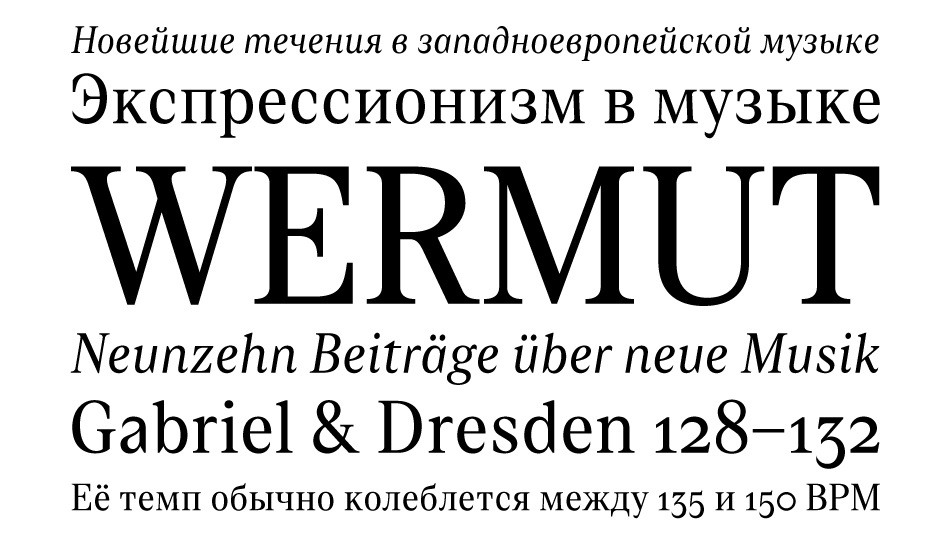
Журнал «Шрифт» • Десять шрифтов с кириллицей 2016 года
Почему бы в мае не вспомнить о прошедшем 2016 годе? Тем более что он был насыщен событиями как на глобальной, так и на локальной шрифтовой сцене. Вот некоторые из них. На конференции ATypI в Варшаве была представлена технология вариативных шрифтов, и, хотя об особенностях её применения споры не унимаются, очевидно, что отчасти будущее типографики где-то там.
Возможно, ответом на глобальный вызов Monotype (за покупкой FontShop последовало ещё два крупных приобретения: платформы визуального маркетинга Olapic и стартапа Swyft Media, зарабатывающего на эмодзи) явился Type Network — инициатива Font Bureau (Дэвид Берлоу и Роджер Блэк). В компании собран выразительный состав менеджмента и экспертного совета (в который вошли Дэвид Берлоу, Мэтью Картер, Петр ван Блокланд, Сайрус Хайсмит и другие).
Российский ландшафт тоже становится во многом интереснее: «ПараТайп» перезапустил магазин шрифтов Fonts.ru, в котором пользователям предложено сразу несколько оригинальных сценариев поиска и выбора шрифтов.
Разобравшись с флешбеком 2016-го, вернёмся к нашему ежегодному обзору. Условия выбора проектов остались прежними: шрифт должен содержать набор кириллических знаков, право на его использование должно быть доступно для приобретения любому желающему, дата выпуска — не ранее января и не позднее декабря 2016 года. На этот раз дополнительно к десятке мы решили собрать небольшой арьергард из 9 шрифтов, а авторам шрифтов задали пару вопросов:
Итак, все 10+9 в алфавитном порядке☟
Дизайнеры: Арина Алафердова, Дмитрий Кирсанов.
Издатель: ParaType, Россия
Крупнокегельная версия шрифта Baskerville вышла в компании «ПараТайп» в сентябре 2016 года в комплектах Display и Poster. Базовые параметры гарнитур унаследованы от ITC New Baskerville, так что они составляют хорошую пару к 8 начертаниям от Джона Квартанта и Ко, сделанным в ITC в 1972 году (кириллический набор знаков был создан Тагиром Сафаевым в 1993-м). Обострённый контраст, зауженные пропорции знаков, тонкие детали (особенно примечателен курсив в Baskerville Poster) предполагают работу в крупных кеглях — и в этом масштабе Baskerville Display & Poster приобретают неприличную красоту и изящество. Можно сказать, что авторам удалось максимально претворить стремление Джона Баскервиля к тонкой и выразительной форме. Среди прописных знаков курсива можно обнаружить и альтернативные формы со свошами и росчерками, напоминающими нам о том, что сам Баскервиль был прекрасным каллиграфом.
Шрифты Baskerville и сегодня остаются рабочей лошадкой многих типографов. С советских времён (если говорить о кириллической версии) комфортные пропорции, спокойные и привычные формы этой гарнитуры встречаются на страницах детских книг, художественной литературы, документальной прозы, журналов. Эти шрифты сложно назвать остроактуальными, но они всегда будут присутствовать в арсенале дизайнера, оформляющего книгу. И теперь с появлением тщательно отрисованных крупнокегельных версий дело остаётся за умелым применением этих шрифтов не только в заголовках и на титульных страницах книг, но и в журналах, инфографике и прочих жанрах — без стеснения в кеглях и размерах.
Дизайнеры: Ольга Панькова, Илья Рудерман. Издатель: type.today, Россия
Этот неогуманистический гротеск с беспрецедентным для текстового шрифта количеством лигатур (как в латинице, так и в кириллице) был разработан по заказу журнала «Большой город». В интервью с Ильёй Рудерманом мы уже рассказывали о роли этого шрифта в издании: «Гротеск Big City сделал немало и для литературного, и для гражданского образа журнала. Во многом этому способствовала актуальная типографика с долей самоиронии, что в целом отвечало и духу индивидуальности личности, и демократизму, которые провозглашал БГ». На тот момент гарнитура содержала 11 начертаний (9 прямых и два курсивных). В 2009 году Big City стал победителем международного конкурса Современная кириллица. Шрифт долгое время оставался в эксклюзивном использовании редакцией журнала, затем начался долгий процесс доработки гротеска с участием Ольги Паньковой для публичного релиза под лейблом
В 2016 году шрифт был представлен в девяти насыщенностях (от Hairline до Heavy) с соответствующими курсивами (всего 18 начертаний). В новой версии уточнён рисунок знаков, добавлена капитель, новые лигатуры и неалфавитные символы. Если принимать во внимание, что гарнитура поддерживает более 100 языков, а лигатуры присутствуют не только в строчных, но и в прописных знаках и в капители, то грубый арифметический подсчёт даёт более 2000 лигатур в одном начертании. Умножая на общее количество насыщенностей, мы получаем астрономический объём работы, которая была проделана для того, чтобы выпустить шрифт в продажу.
Типографический потенциал этого гротеска выглядит весьма впечатляющим. Кроме необъятного количества лигатур он оснащён символами, чувствительными к регистру, всеми видами цифр, числительными, дробями, индексами, математическими знаками ключевых валют.
Стимулом к работе послужила моя стажировка в CSTM Fonts, и я была счастлива, что Илья и Юра (Илья Рудерман и Юрий Остроменцкий.
— Прим. ред.) доверили мне именно этот шрифт. Во-первых, я фанат одноимённого журнала и до сих пор храню много номеров, а во-вторых, после долгой работы над Пулитцером было очень интересно поработать с гротеском, и особенно с лигатурной частью. Поначалу страшнее всего было вносить даже минимальные изменения в контуры, ведь этим шрифтом долго набирали журнал и он прекрасно работал! Но поскольку я всё делала под чётким руководством Ильи, больших сложностей не возникало. Думаю, всё, чему я научилась в процессе создания такой большой семьи, можно считать достижениями.
Дизайнер: Александра Королькова. Издатель: FontFont, Германия
Наследник шрифта Belladonna (эксклюзивный проект для журнала Italia), гарнитура FF Carina — это вариация на тему антикв нового стиля XVIII–XIX веков. Монументальная симметрия и статика, высокий контраст, зауженные пропорции знаков — все признаки, присущие дидонам, мы видим и здесь.
Однако изобретательная работа с остроконечным пером привела к уникальному образу. Необычная пластика графем, наплывы овалов с энтазисом, чернильные сталагмиты и сталактиты засечек в прописных C, E, F, G, S, T, Z, кокетливые капли в строчных знаках — и вся неоклассика летит к чёрту, а взгляду открывается эстетика журнального леттеринга 1970-х в исполнении Герба Любалина и, например, шрифт ITC Tiffany Эда Бенгета.
Декоративность внедрена в шрифт по его же законам — лигатуры, своши, минускульные цифры и некоторые альтернативы развивают характер шрифта. Отдельного отметим альтернативный ноль в волос толщиной и кириллические лигатуры, сделанные без стремления соединить всё со всем. FF Carina поддерживает почти сотню языков, она простроена в трёх начертаниях (Regular, Bold, Black), содержит дроби и математические знаки (хотя сложно предположить, что гарнитуру будут использовать в контексте, в котором потребуются дроби и индексы).
…Арт-директор «ПараТайпа» публикует шрифт в «ФонтШопе»? В этом нет никакой конспирологии. Предложение лицензировать будущий шрифт поступило автору от FontShop на конференции ATypI ещё в 2008 году, и спустя годы Александра сдержала своё обещание.
Дизайнер: Валерий Голыженков. Издатель — type.today, Россия
Акцидентное начертание шрифта Futura Display (как и формы Futura Black), выпущенное Паулем Реннером в 1932 году, очевидно, уже навсегда останется в тени основного комплекта стилей этого геометрического гротеска. Более того, этот квадратный упрощённый шрифт в современной логике проектирования шрифтовых семейств не имеет общей конструктивной и графической основы с Футурой.
Обращение Валерия Голыженкова к неочевидной стороне Футуры привело к проверке потенциала и возможностей этой графики. Сначала First Prize производит впечатление реплики на реннеровские формы, но, разглядев детали проекта, понимаешь, что здесь работа велась совсем в другом направлении.
Автор ставит перед собой задачу «генетического» эксперимента. Да, в основе работы — жёсткая логика геометрического гротеска (First Prize лишён даже скруглений внутренних овалов, а внутрибуквенное белое вырублено под прямым углом), но самое нтересное начинается с момента внедрения в эту графику конструкций наклонного и прямого курсивов (Bold Italic, Bold Upright). Добавить сюда цитирование некоторых особенностей старостильных антикв (верхние выносные элементы выше прописных, минускульные цифры), игры с начальными и концевыми росчерками — и идея доводится до возможного абсолюта.
В результате получился акцидентный шрифт, который в любом макете решительно возьмёт на себя роль солиста. И если начертание Bold действительно напомнит нам о Реннере, то Bold Italic и Bold Upright — это настоящий Голыженков. Если вам доводилось видеть его быстрые наброски шрифтовых форм (на бумажных скатертях в кафе, например), то вы поймёте, что синтез каллиграфии и шрифтовой инженерии — это характерная особенность его авторского темперамента.
Шрифт способен держать как экстремально крупные кегли, так и среднекегельный набор (в умеренных количествах) и обладает всем потенциалом для развития в сторону светлых начертаний. В любом случае First Prize уже занял место в ряду состоявшихся шрифтовых экспериментов.
Импульсом для начала работы могу назвать два момента. Первый — желание дать новую жизнь одному из моих старых шрифтов. В результате FirstPrize 2000 года выпуска был полностью перестроен. Второй момент — это интерес, который проявили к шрифту Илья и Юрий (Илья Рудерман и Юрий Остроменцкий. — Прим. ред.) во время просмотра и обсуждения кандидатов для релиза на площадке type.today. Признаюсь, без их поддержки шрифт мог бы надолго задержаться в столе среди прочих набросков. На сегодня удалось подготовить две группы связанных между собой начертаний, каждая из которых привязана к FirstPrize Bold.
Одна группа — это начертания зауженных пропорций, вторая состоит из сильно сжатых начертаний.
Сложности? Это, наверное, самый объёмный из моих проектов, и сложнее всего было на стадии технической разработки и тестирования, когда все основные идеи были уже реализованы — нужно было не отвлекаться на другие, более творческие задачи.
Дизайнеры: Винсент Чан, Кристиан Шварц, Илья Рудерман (кириллица). Издатель: Commercial Type, США
Дизайнеры Винсент Чан и Кристиан Шварц спроектировали этот гротеск в 2008 году по заказу Кристофера Мартинеза, арт-директора журнала о моде и стиле T (The New York Times Style Magazine). Журнал Т укоренён в культуре и визуальной истории большого американского мегаполиса. Хотя он был запущен в 2004 году, связь издания с NYT наводит на соображения, что каждый редизайн Т немыслим без доли консерватизма и поисков интеллигентных ходов.
Первый шрифт семейства Giorgio (2007) с засечками, который арт-директор T-magazine Кристофер Мартинез наметил для заголовков, получился коктейльной гарнитурой с благородной историей. В нём смешаны высокий контраст, геометричность, несколько эксцентричных деталей в альтернативных знаках. Характерная особенность — минимальная разница между высотой строчных и прописных знаков и короткие выносные элементы. Отсылка к 1930-м была очевидной — по словам авторов Giorgio, многие решения они переняли из гарнитуры Corvinus (Bauer Type, ок. 1935) швейцарского дизайнера Имре Райнера. Это было время ненависти к орнаменту — Корвинус сделан минималистично и обладал своеобразным ритмом.
Генетика Giorgio Sans того же порядка — узкий гротеск с короткими выносными элементами, который в наборе сбивается в плотные строки, напоминающие о типографике модных журналов 20-х и 30-х годов.
Он более «полиграфичен», универсален и не претендует на связь с историей, городской средой и афишами века джаза. Отдельный сет круглых и более широких прописных знаков позволяет играть с ритмами заголовков — приём, которым уже увлекались журнальные дизайнеры (не стоит забывать, что шрифт был сделан для макета десятилетней давности). Кроме того, латиница содержит четыре альтернативных знака G, Q, R и g, а в кириллице только буквам Я, я повезло иметь вариацию.
Можно сказать, что это шрифт для ручного набора — диапазон насыщенностей (9 начертаний с курсивами) предполагает побуквенную сборку акциденции, взаимодействие её с графикой и фото, тонкую работу с белым пространством листа, огромным пятном, конструкцией. Чем громче, тем лучше, но нет ничего скучнее монотонного текста, аккуратно набранного Giorgio Sans в небольшом кегле.
Дизайнеры: Манвел Шмавонян и Александр Любовенко. Издатель: ПараТайп, Россия
Mediator — необходимое и ожидаемое приближение к универсальным гарнитурам вроде Frutiger или Univers, которых по-прежнему не хватает на рынке кириллицы. Это неогуманистический гротеск со спокойной (на первый взгляд) пластикой, и его главные качества — удобочитаемость в мелких кеглях и лёгкость сочетания с книжными антиквами различного рисунка и темперамента.
У шрифта открытая апертура, разница между высотой прописных и строчных знаков существенная, как и высота выносных элементов. Прописные буквы равноширинные; образ шрифта в кириллическом наборе чем-то напоминает Humanist 531 (кириллическая версия шрифта Syntax Ганса Эдуарда Мейера, 1968). Возможно, это уже авторский почерк — оба шрифта были сделаны Манвелом Шмавоняном. Вопросы вызывают разве что зауженные начертания Narrow и Condensed: в таких тисках динамичные формы начинают «скрипеть», все изгибы, дуги, диагонали деформируются, а размашистые выносные элементы сопротивляются попыткам собрать немногословную композицию.
По словам издателя, Mediator — незаметный шрифт, но, по нашему мнению, в текстовых кеглях он достаточно эмоционален и выводит свою, совсем не медитативную мелодию. Это нужно учитывать при выборе шрифта в качестве как основного, так и вспомогательного инструмента для набора. Гарнитура содержит 30 начертаний: 8 прямых и 8 курсивных от Thin до Black, 7 зауженных и 7 узких от Thin до ExtraBold. В комплекте минускульные цифры во всех начертаниях и капитель в прямых начертаниях нормального диапазона.
У меня давно зрела мысль сделать шрифт большого диапазона с довольно широкими пропорциями. Я и раньше проектировал шрифты с большим количеством начертаний, но в таком диапазоне — начиная с Thin до Black — впервые. По большей части я проектирую текстовые шрифты. И в этот раз мне хотелось создать современный текстовый гротеск. Сложность была в том, что очень трудно выделиться в том количестве шрифтов, которые уже существуют и разрабатываются сегодня дизайнерами.
Я стараюсь выделяться отточенностью моих шрифтов. Насколько это у меня получается — судить не мне.
Дизайнеры: Петер Билак, Ирина Смирнова (кириллица). Издатель Typotheque, Нидерланды
Петер Билак поставил перед собой довольно практичную задачу — создать рациональный шрифт, который работал бы в длинных текстах так же хорошо, как и в заголовках и навигации. Подобно шрифтам для систем ориентирования, November спокоен и лишён ярких отвлекающих деталей. «Порой шрифт должен просто хорошо справляться со своими обязанностями», — комментирует Билак свою задачу.
Достаточно взгляда на состав шрифтовой семьи, чтобы убедиться в её мультифункциональности. Три группы начертаний (Normal, Condensed, Compressed) в диапазоне от Hairline до Black; капитель, минускульные цифры, индексы, регистрозависимые альтернативные знаки дадут необходимую свободу дизайнеру в работе с любой типографической задачей.
Добавить к этому кириллицу (дизайн Ирины Смирновой), греческий и иврит (консультации Даниэля Грамера) — и применение шрифта расширяется до 200 языков.
С набором массы от начертания к начертанию шрифт обретает темперамент, проявляя хоть и сдержанный, но довольно открытый и дружелюбный нрав. Среди цифр на себя обращают внимание 6, 8 и 9, которые, будто игнорируя соседей, выведены из круга с геометричной точностью. В светлых начертаниях видна точная работа Билака с характером овалов и формой. Позволив себе грубое обобщение, этот шрифт можно было бы назвать голландским DINом, в котором верх берёт не инженер, а прагматичный художник.
Работа над кириллицей к November шла на удивление легко. Не знаю, помогал ли мне предыдущий опыт — работа над суперсемейством Greta Sans или сам рисунок шрифта.
Единственная форма, которая нашлась не сразу, — это строчная б. Лаконичность форм не позволяла добавить привычный изгиб вверх в окончании выносного элемента. Диагональный штрих требовал другого среза, а горизонтальный выносной элемент без изгиба делал форму больше похожей на шестёрку. Я нашла тот минимальный наклон, который создал необходимое движение по диагонали вверх и позволил закончить штрих строго вертикально. Когда я стала тестировать готовый шрифт, то поняла, что November действительно не обращает на себя внимания во время чтения. Чёткий и ровный ритм, вертикальный характер форм помогали сконцентрироваться, а читать в мелком кегле было на удивление легко. Закончилось тем, что деловой и незаметный November стал моим шрифтом по умолчанию в текстовом редакторе.
Дизайнер: Елена Новосёлова. Издатель: type.
today
Авторское прочтение Еленой Новосёловой шрифтовой классики. Интерпретации на тему шрифтов Бодони можно найти в каталогах множества словолитен. Одной из самых убедительных работ до сих пор считается версия, выполненная для компании ITC в середине 1990-х годов под руководством Самнера Стоуна, которая включает в себя несколько оптических начертаний, основанных на трёх оригинальных кеглях в 6, 12 и 72 пункта. Совсем недавно яркий эксперимент на тему шрифтов Bodoni был проведён в проекте Parmigiano, выпущенном студией Typotheque (мы писали об этом в предыдущем обзоре).
Для версии NWT Bodoni автор выбрал образцы текстовых кеглей в 9 и 12 пунктов, что предполагает использование шрифта в длинных текстах. Однако стоит с осторожностью использовать шрифт в кегле ниже 12-го: регулярное начертание создаёт плотный и густой набор при довольно высоком контрасте, что может быть критичным при растискивании краски при печати на рыхлой бумаге.
Текстура набора равномерна, а образ текста напоминает о шрифте Filosofia Зузанны Личко. В деталях же эти шрифты различаются принципиально. Если формы Filosofia смягчены, то NWT Bodoni принципиально обострён (вертикальные засечки C, E, F, G, S, T, Z — это острые клинки).
Чистота и стремительность контуров в шрифте Елены Новосёловой создаёт ощущение скорости внутри статичных конструкций знаков. Эта скорость, например, проявляет себя в ярких курсивных минускульных цифрах. Минускульные цифры можно смело причислить к основным достоинствам гарнитуры: тугие контуры 2, 3, 5 сложно не узнать в ряду подобных. Также обращает на себя внимание и характер формы внутренних овалов NWT Bodoni — они существенно заострены, тогда как в мелких кеглях многих шрифтов Bodoni из-за стремления вместить больше пространства чаще встречаются оквадраченные варианты.
Про этот шрифт я думала давно, особенно завораживала кириллица, нарисованная Бодони. Когда издательство Taschen выпустило Manuale Tipografico, я купила книгу. Начала изучать, сканировала, сравнивала рисунок для разных размеров и нарисовала свою интерпретацию. Сложность заключалась в том, что я рисовала контрастный шрифт, но этот контраст не должен был мешать чтению, а характерный рисунок Бодони требовалось сохранить.
Дизайнеры: Яна Кутьина, Андрей Белоногов, Валерий Голыженков. Издатель: Ателье Otadoya
Удачно подобранные и представленные зрителю легенда и образ шрифта, как правило, при первом знакомстве дают проекту несколько очков вперёд. Triplet — не исключение. Союз Яны Кутьиной и Андрея Белоногова в этом проекте дополнен участием Валерия Голыженкова. Триптих стал ключевой идеей проекта. «Нестандартный костюм-тройка для настоящих оригиналов», «Ультрасовременность и винтаж в одном флаконе», «Единство трёх независимых начертаний» — этими метафорами встречает зрителя авторская презентация.
Оставим оригиналов в костюме-тройке в стороне и посмотрим на два других тезиса. Triplet действительно производит впечатление одновременно и свежести (особенно справедливо это для кириллицы), и определённого винтажного флёра. Основой графики Triplet послужили шрифты, ставшие популярными в XIX–XX веках по обе стороны Атлантики, типа Latin Antique и Breite Etienne. Переходная форма окончания основных штрихов (что-то среднее между наплывом и засечкой), конструкции знаков, форма овалов и характерная графика основного начертания (Triplet Erste) создают настроение шрифта. Образ кириллицы подобран тщательно и уместно — она не противоречит логике, заданной латиницей.
«Единство трёх независимых начертаний» и правда формирует цельную картинку шрифтовой семьи. Однако сами начертания, несмотря на индивидуальные графические особенности в узком (Zweite) и курсивном (Dritte) комплектах знаков, едва ли можно назвать независимыми.
Они производят впечатление последовательной и довольно изобретательной работы в рамках одной шрифтовой идеи. Собственно говоря, это вопрос терминологии.
Этот яркий проект в определённом смысле вызывает графического дизайнера на дуэль и требует от него изрядной сноровки. Но очевидно и то, что появление таких проектов расширяет артистический диапазон шрифтового мира.
Импульсом послужило желание сделать что-то совместно — нетривиальное, бодрое, желательно быстрое (мечтать не вредно), но нелегковесное. У каждого из нас имелся груз в виде энного количества затянувшихся проектов — и нести тяжело, и бросить жалко. А вот придумать-сделать-отпустить — этого нам всем не хватало. Начали с подбора музыкального референса, соответствующего настроению нашего воображаемого шрифта. В поисках визуального образа наткнулись на сдёрнутую из чьего-то инстаграма картинку с образцом шрифта, и нам показалось, что это круто.
Как выяснилось позже, он выпускался различными словолитнями на рубеже XIX–XX веков под названием Latin Antique. Эта единственная картинка задала направление для Erste, а затем пришла идея про тройственность, и дальше мы двигались эмпирически.
Немало внимания уделили неалфавитной части: пуговицы, запонки, торчащий из кармана уголок платка — иногда второй план не менее важен, чем первый. Мы осознанно искали безальтернативные решения, балансировали на грани разности и созвучии начертаний. Старт был очень бодрый и воодушевляющий, а потом снова выяснилось, что делать шрифт — это довольно нудно и скучно. Но было поздно!
Дизайнеры: Вячеслав Кириленко, Гаянэ Багдасарян. Издатель: Brownfox, Россия
По рецепту античных времён в состав вермута — креплёного вина, настоянного на альпийской полыни, — входит целый набор разнотравий: тысячелистник, мята, корица, кардамон, чёрная бузина, мускатный орех и прочее.
Сложно представить более подходящий вариант для названия этого шрифта: в образе и деталях Wermut смешан букет шрифтовых мотивов, что даёт как автору, так и типографу определённую свободу интерпретаций.
Wermut — яркий акцидентный шрифт, которому предписано использование в крупном и среднем кеглях. Всего два начертания (прямое и курсивное) проверят на прочность намерения дизайнера. Но парадоксальным образом в текстовом наборе, начиная с 7-го кегля, этот шрифт хорошо держит достаточно убористую, ёмкую строку. В характере антиквы при желании можно рассмотреть отсылки к узким крупнокегельным версиям так называемых «латинских» шрифтов, которые были популярны во Франции со второй половины XIX до середины XX века, или же уловить ноты немецких вариаций начала XX века на тему гарнитуры Lateinisch. Некоторые формы укажут и на Times New Roman, а кому-то вспомнятся оригинальные буквы Роже Эксофона.
Набор ассоциаций можно перечислять бесконечно и постоянно возвращаться к пряному букету разнотравий, собранному авторами шрифта. Неизгладимое впечатление на зрителя производит общая пластика с острыми элементами в прописных и строчных знаках, а также форма строчной а. Wermut — определённо художественный манифест, занимающий уникальное место в современном типографическом арсенале.
В какой-то момент мы немного устали от брутальных гротесков, и нам захотелось сделать антикву. Образ Вермута вначале сложился словесно, как если бы мы описывали характер человека. Он должен был быть неоднозначным, изящным, строгим, вызывающим, металлическим, колючим, но и немного плавно-растительным. Немного декадентским, но с классической основой. Мы стали искать соответствия этим ощущениям в шрифтах и сошлись на том, что ищем что-то между Скотч-антиквой и Таймсом.
Довольно большой промежуток во времени и большая разница в визуальном облике, но это именно то, к чему мы всегда стремимся: соединить несоединимое. Буква а, главная стилеобразующая буква, совсем не похожа ни на Таймс, ни на Скотч Модерн. Именно на ней лежит задача презентации образа шрифта, она должна быть самой яркой, а все остальные буквы более сдержанными. Это становится очевидным в наборе: буква а рассыпана по тексту и всё время колет ваш взгляд.
И ещё несколько шрифтов с кириллицей 2016 года
Дизайнер: Захар Ящин (FontaZY). Издатель: ParaType, Россия•Энергичный скрипт со множеством лигатур. Неожиданно редкий зверь в кириллическом сегменте, при этом западный шрифтовой рынок, пожалуй, перенасыщен подобными проектами.
Дизайнеры: Эммануаль Рей, Алексей Ваняшин (кириллица). Издатель: Swiss Typefaces, Швейцария•Мириад альтернатив в каждом начертании этого геометрического гротеска до сих пор поражает воображение.
Теперь все прямые начертания содержат и кириллицу.
Дизайнер: Ксения Белоброва. Издатель: MyFonts, США•Ещё одно торжество контекстуальной замены и фичи Liga. Примечателен контраст между винтажными, аккуратно выписанными строчными буквами и более прямолинейными прописными.
Дизайнеры: Илья Рудерман, Юрий Остроменцкий. Издатель: type.today, Россия•Обещанная авторами в 2015 году текстовая версия яркой и актуальной антиквы, переосмысляющей исторические образцы.
Дизайнеры: Дэвид Джонатан Росс, Мария Дореули (кириллица), Джордж Трентафиллакос (греческий). Издатель: djr.com, США•Правильный Дикий Запад в исполнении Дэвида Джонатана Росса. А если точнее — классический кларендон, в котором все свойства этой стилистической подгруппы доведены до предела.
Дизайнер: Петер Билак, Никола Джурек (консультации), Мария Дореули (консультант по кириллице), Джерри Леонидас и Ирен Влачау (консультанты по греческому).
Издатель: Typotheque, Нидерланды.•Почерки Петера Билака (формальный, небрежный и с нажимом) в цифровом воплощении.
Дизайнер: Петер Билак, Никола Джурек (консультации). Издатель: Typotheque, Нидерланды.•Идеальный шрифт для последующего вырезывания букв круглой фрезой со сменными лезвиями разного диаметра.
Дизайнеры: Дэвид Бржезина, Слава Евчинова, Титус Нимет, Патум Эгодаватта. Консультанты: Ирен Влачау (греческий), Максим Жуков (кириллица). Издатель: Rosetta.•Гротесковая половина важной шрифтовой системы с огромным количеством начертаний и интересным подходом к проектированию пары антиква—гротеск.
Дизайн: Swisstypefaces, Алексей Ваняшин (кириллица), Паскаль Зогби (арабский). Издатель: Swisstypefaces.•Покой и воля в типографическом воплощении — теперь и с кириллицей.
Редакция благодарит всех авторов шрифтов за предоставленные материалы.
Цифра «10» для обзора нарисована Яной Кутьиной и Андреем Белоноговым.Но это ещё не всё. В январе коллеги из type.today при нашем участии составили полный список шрифтов с кириллицей 2016 года.
10 лучших шрифтов 2017 года | GeekBrains
Портал Graphicpear рекомендует шрифты с засечками.
https://d2xzmw6cctk25h.cloudfront.net/post/1467/og_cover_image/00512080505678c8387f737c3b724306
Палитра шрифтов, используемых верстальщиками и дизайнерами, расскажет об их профессионализме больше, чем увесистое портфолио. Поэтому специалисты стараются добавлять в рабочий арсенал новые и интересные шрифты. Скучным Arial или заезженной Verdana никого не удивишь. Представляем подборку лучших шрифтов 2017 года по версии портала Graphicpear.
Элегантный шрифт, начертание которого напоминает стилистику 18 века. Выполнен в схожей стилистике шрифтов Baskerville и Boydell Shakespeare. Автор шрифта — Клаус Эггерс Соренсен.
Это высококонтрастный шрифт с засечками, который обычно используется для заголовков, названий и титров. Желательно использовать в паре с Georgia для основного текста.
Шрифт создан историком и преподавателем МГУ Алексеем Крюковым в 2007 году. Входит в семейство Theano и изначально создавался только для греческого языка. Но впоследствии была добавлена латынь и кириллица. Шрифт доступен для бесплатного использования. Относится к категории новая антиква, с засечками.
Шрифт отличается нестандартным дизайном, подходит для логотипов, названий, журнальных разворотов. Чистый и высококонтрастный шрифт. Включает семь стилей.
Это шрифт класса Slab (плоские засечки), часто используется в веб-проектах. Был разработан Атипо и Марией Рамос.
Шрифт был придуман еще в 1989 г. дизайнером Кэрол Туомбли в двух начертаниях: нормальном и жирном. Он имитирует древнеримский монументальный шрифт, которым сделаны надписи на пьедестале колонны Траяна.
Очень часто используется на постерах к фильмам.
Шрифт был создан еще во времена Просвещения. Его автором стал член семьи Дидо, знаменитой династии типографов и бумажных фабрикантов. Имеет четкое и ясное начертание и остается тонким текстовым шрифтом для рекламы и книжного дизайна. Похож на Henriade.
Шрифт отлично подходит для лонгридов. На больших полотнах текста он выглядит стильно и легко читается. Отличительные черты: небольшие размеры, сильные засечки и ровный ритм текста.
Это универсальный шрифт с индивидуальными чертами. Был спроектирован Джо Принцем и представляет собой современную форму гибкого Slab Serif (шрифты с плоскими засечками). Поставляется с четырьмя начертаниями и содержит восемь шрифтов в семействе Klinic Slab.
Бесплатный шрифт с засечками представляет собой смесь семейства Bodoni и Dala Floda. Его создали для повышения оригинальности шрифтов с засечками. Для этого улучшили изгибы стандартных шрифтов с засечками и добавили дополнительные начертания.
Широко используется для плакатов, книг и больших форматов. Семейство шрифтов Butler содержит 334 символа, семь трафаретов и семь начертаний. Он также имеет текстовые фигуры, фракции, лигатуры и пр.
Тщательно продуманный шрифт с засечками, который передает стилистику римских шрифтов, не боящихся времени. Fanwood поставляется с курсивом и римским стилем, оба они оптимизированы для экранов. Используется в заголовках и текстах, легок для чтения с экрана. Был разработан Барри Шварцем, распространяется под лицензией SIL Open Font для бесплатного использования.
Finches — элегантный шрифт с засечками и курсивом с исключительно красивыми изгибами, которые придают ощущение роскоши и элегантности. Шрифт выглядит профессионально и помогает хорошему проекту повысить уровень. Используйте его для оформления книжных обложек, постеров, постов в соцсетях.
Migur — строчный шрифт, созданный для использования в журнальных проектах. Шрифт получил пару наград и был выбран проектом Behance одним из лучших. Он доступен бесплатно для личного пользования. Добавляйте декоративные элементы, чтобы повысить его привлекательность.
Это была подборка от Graphicpear. А какие шрифты любите вы? Поделитесь в комментариях.
100 коллекций шрифтов для различного применения в дизайне: rentafont — LiveJournal
Это четвертый из десяти постов с коллекциями шрифтов Rentafont, описанных разными способами.
Одно из главных преимуществ Rentafont – уникальный шрифтовой поиск с очень детальным описанием шрифтов из 12000 уникальных ключевых слов и опций на русском, английском и украинском языках. Таким способом описано более 3000 шрифтов с латиницей и кириллицей.
Такие данные будут полезны при обучении начинающих дизайнеров и искусственного интеллекта. Если вы генерируете дизайн с помощью алгоритмов или нейросетей, исходя из параметрического ТЗ, вам пригодятся шрифты, релевантные разным видам деятельности, техническим параметрам и особенностям аудитории.
Место в макете- Акциденция (яркие шрифты для небольших надписей) (2428 шрифтов)
- Заголовок (заголовочные шрифты для шапок, обложек) (2254 шрифтов)
- Логотип (характерные шрифты для логотипов) (1137 шрифтов)
- Основной набор (разборчивые текстовые шрифты) (1030 шрифтов)
- Выделения (жирные и наклонные текстовые шрифты) (740 шрифтов)
- Инфографика (понятные шрифты для инфографики) (461 шрифтов)
- Инициал (декоративные шрифты для буквиц) (383 шрифтов)
- Примечания (курсивные текстовые начертания) (275 шрифтов)
- Подписи (текстовые шрифты для сносок) (10 шрифтов)
Эти коллекции являются ответами на поисковые запросы из одного ключевого слова.
Уникальный поиск Rentafont состоит из 4 групп фильтров и базы словесных описаний, повторяющих и значительно дополняющих эти фильтры.
Чтобы проверить, есть ли здесь нужное вам описание, используйте поиск текста в вашем браузере. Если не нашли то, что искали, пожалуйста, напишите об этом в комментариях.
По поводу доступа к полной обновляемой базе описаний шрифтов, API шрифтового поиска, датасетам для обучения нейросетей пишите на .
Другие посты из серии1. 200 коллекций шрифтов разной формы
2. 200 коллекций шрифтов по возрасту, полу, настроению
3. 200 коллекций шрифтов для разных отраслей
5. 100 коллекций шрифтов из разных стилей и эпох
Рубленые шрифты и шрифты с засечками ‹ Виртуальная школа графического дизайна
Продолжение. Читать начало статьи…
После непродолжительной отпускной паузы, продолжаю серию статей о журнальном дизайне. В предыдущей статье я писал о модульной сетке, как об одной из основ дизайна печатных изданий.
Теперь поговорим о шрифтах.
Даже неискушенный глаз при взгляде на любой печатный текст, может заметить, что одни шрифты имеют засечки, а другие — нет. Наличие или отсутствие этих засечек и есть главное отличие двух основных групп шрифтов.
Засечки в шрифтах представляют собой короткие, обычно перпендикулярные штрихи, которыми начинаются и заканчиваются основные штрихи знака. В старой литературе иногда называется «отсечка». Засечки бывают односторонними и двусторонними. Их форма может быть разнообразной: треугольной, прямоугольной, закругленной, декоративной, в виде тонкой горизонтальной линии и т.д. Засечки могут быть скругленными в месте соединения с основным штрихом, а могут присоединяться под углом без скругления.
Шрифты без засечек называются рублеными. В Англии, и Франции такие шрифты чаще называются Sans Serif, в Америке Gothic, в Германии Grotesk. Как правило, гротески имеют основные и соединительные штрихи практически одной толщины (неконтрастные) или с малозаметной разницей в толщине штрихов (малоконтрастные).
Шрифты с засечками также называют антиквой. В Англии, США и Франции такие шрифты чаще называются Serif.
Термин «Антиква» (Antiqua) заимствован из немецкого языка (где он обозначает любой шрифт прямого начертания) и указывает на его древнее (античное) происхождение, поскольку каролингское письмо VIII–IX вв., лежащее в основе гуманистического письма, в эпоху Ренессанса ошибочно принималось за подлинное письмо античности. Антиквенные шрифты обычно делятся на Антикву старого стиля, Переходную антикву и Антикву нового стиля, а также Брусковую антикву.
Рубленые шрифты выглядят более современными, а на практике они более удобны для дизайнерской работы. Например, для построения логотипа. В них легче управлять межбуквенными расстояниями. Крупные текстовые элементы, набранные таким шрифтом, воспринимаются единым пятном, т.е. целостно. Вот почему подавляющее большинство заголовков создают именно шрифтами без засечек. Основной же мелкий текст статей, как правило, набирают шрифтами с засечками. Почему так, а не наоборот?
Дело в том, что рубленые шрифты воспринимаются как более устойчивые, основательные и массивные, тогда как шрифты с засечками легче читаются. Статья, набранная таким шрифтом, читается быстрее и свободнее, т.к. засечки, как бы облегчают движение глаз от буквы к букве.
Конечно, это правило довольно общее. Существуют газеты и журналы, где оно не соблюдается, но любое исключение из правил должно быть оправдано.
Если вы точно знаете и понимаете, почему в вашей работе заголовки должны быть набраны шрифтом с засечками, а мелкий текст, наоборот, рубленым шрифтом, тогда вы вправе наплевать на то, что пишут в учебниках по типографике. Но на заре вашей дизайнерской карьеры, я бы посоветовал вам просто поверить, что все эти умные учебники писали отнюдь не дураки…
Самый важный фактор в выборе шрифта для основного текста — его читабельность. Печать газеты может быть неудовлетворительна, и поэтому использование шрифта с засечками будет неразумно. Если печатная краска не ложится на странице ровным слоем, то засечки букв, возможно, не будут даже видны. В таких случаях применение красивого рубленного шрифта будет более уместно. Качество печати журналов, как правило, значительно выше, и такая проблема вряд ли возникнет.
Единственный способ определить наиболее удобочитаемый шрифт для вашего основного текста – это эксперимент и отбор образцов различных шрифтов, учитывая технические возможности типографии. Рассмотрите печатные образцы и решите, какой шрифт является наиболее четким.
Выбрав шрифт, используйте его последовательно на всех полосах журнала. Стиль заголовка должен быть прост. Все заголовки выполняйте одним и тем же шрифтом. Заменить его на другой шрифт стоит лишь в случае осознанной необходимости. Например, в отдельных рубриках, которые нужно выделить среди всех остальных материалов.
Вместе с тем, вы можете разнообразить внешний вид заголовков при одном шрифте, используя различные размеры, стили и цвета.
Последовательное использование шрифта служит ориентиром для читателей. Если заголовки статей определенного раздела, набранные одним шрифтом, а заголовки другого раздела – другим шрифтом, то читатель сможет с первого взгляда различать эти разделы.
В заголовках не используйте только прописные буквы!
Как показывают исследования, человек читает и воспринимает слова, напечатанные только заглавными буквами, намного дольше, чем слова, состоящие из прописных и строчных букв. Если вы все же решите использовать в заголовке ведущей статьи только заглавные буквы, то увеличьте размер шрифта так, чтобы уменьшить неудобство восприятия текста.
Используйте выбранный шрифт достаточно большого размера, чтобы его легко можно было читать. Помните, что текст статей должен легко восприниматься читателем. Если текст напечатан слишком мелко то, это позволит разместить больше слов на странице, но вместе с тем, затруднит их зрительное восприятие. Традиционно в российских газетах текст печатался 8-м кеглем, однако сейчас наблюдается тенденция к увеличению размера шрифта до 9 — 9,5.
Определитесь с межбуквенными интервалами (трекингом).
Если расстояние между буквами слишком мало или, наоборот, велико, то слова будет трудно читать и понимать. Найдите оптимальное межбуквенное расстояние и используйте его постоянно во всем проекте.
Тот же самый принцип применяется и при выборе междустрочного расстояния (интерлиньяжа). Наберите текст определенным шрифтом и поэкспериментируйте с интервалом между строками, чтобы выяснить, какой из них наиболее привлекательный и самый удобочитаемый.
Одна из задач интерлиньяжа — создание горизонтального пути для глаз, по которому они возвращаются к началу строки. Дизайн шрифта может влиять на на ширину этого пути. Шрифты с высоким ростом строчных букв, например, обычно требуют дополнительного интерлиньяжа.
Интерлиньяж — важнейший инструмент управления «цветом» текста на странице, поэтому для шрифтов с большей насыщенностью штрихов требуется увеличенный интерлиньяж для того, чтобы осветлить «цвет» текстового блока и сделать его менее плотным.
Установите свой стандарт интерлиньяжа и затем применяйте его постоянно. Не попадайтесь в ловушки, увеличивая размер интервала, когда статья слишком короткая или, уменьшая его, когда текст довольно длинный!
Более подробно о шрифтах читайте на сайте http://ifont.ru/
Продолжение следует…
Поделиться в соц. сетях:
Журнальный шрифт кириллица. Лучшие бесплатные шрифты для дизайнеров
Шрифт, который используется для отображения текста, влияет на его восприятие. Поэтому в этой статье мы собрали лучшие бесплатные шрифты для веб-дизайнеров 2016 года, которые помогут вашим печатным материалам и сайтам выглядеть профессионально.
10 лучших шрифтов с поддержкой кириллицы
Качественные кириллические шрифты нелегко отыскать, но все же сейчас их гораздо больше, чем раньше. Список ниже содержит как распространенные варианты с засечками и без, так и ультраэлегантные шрифты для особых случаев.
5. Oswald — классический чуть сжатый шрифт без засечек, который будет выглядеть хорошо на любых устройствах:
6. Jura — элегантный шрифт со скошенными засечками и круглыми формами, лучше всего подойдет для подзаголовков или основного текста:
7. Exo 2 — универсальный технологичный шрифт с несколькими начертаниями, поэтому его вполне хватит для оформления большинства текстовых элементов на странице:
8. Pompiere подойдет вам, если вы ищите элегантный, но не слишком серьезный шрифт:
9. Aclonica — еще один яркий шрифт для оформления запоминающихся заголовков и печатной рекламной продукции:
10. Museo — шрифт без засечек, который выглядит хорошо при маленьком и большом размере кегля, а значит подойдет как для отображения пунктов меню, так и для основного текста страницы. Доступен бесплатно в вариантах Museo Sans 500 и Museo Sans:
В этой статьи мы привели шрифты для профессиональных графических дизайнеров, которые можно использовать для дизайна страниц или печатных материалов. Большое количество доступных шрифтов часто приводит в замешательство, ведь при этом их еще и нужно правильно сочетать. Вот правила сочетания шрифтов, которые помогут вам справиться с этой задачей:
- Не используйте слишком контрастные шрифты — может получиться так, что каждый из них будет перетягивать внимание на себя, отвлекая читателя от содержания.
- Но и не выбирайте слишком похожие — они будут сливаться, и создавать ощущение незаконченности.
- Создавайте визуальную иерархию — вспомните, как обычно выглядят печатные газеты: в них четко просматривается структура заголовков.
- Не забывайте о контексте — ведь дизайн создается не просто так, а в соответствии с потребностями конкретной компании.
- Не используйте больше трех разных шрифтов на одной странице.
На 2018 год количество качественных бесплатных шрифтов позволяет дизайнерам полноценно работать над задачами, совершенно не стесняясь в выборе. Поэтому мы написали о лучших бесплатных шрифтах.
Студия создает дизайн сайтов и приложений для Android и iOS, и мы будем рады помочь вашему бизнесу привлечь пользователей с помощью уникального и узнаваемого дизайна.
Типографика это искусство, в котором органично сочетаются техника, изобретательность и расчет на перспективу. За редким исключением хороший дизайн подразумевает хорошую типографику. Неважно, над чем работает дизайнер: проектирует сайт или пользовательский интерфейс, работает над макетом брошюры или создает логотип для бренда – везде одним из ключевых элементов успешного проекта будет шрифт. При этом огромное значение имеет не только выбор шрифтов, но и их соответствие друг другу, а также цветовые решения. Вариантов может быть очень много, но от правильного выбора шрифта во многом зависит, будет успешным проект или его ждет провал. Порой достаточно упустить из виду даже второстепенные детали, чтобы свести на нет все творческие усилия, которые были направлены на создание выдающегося дизайна. К счастью, есть множество ресурсов, которые помогут в работе с типографикой.
Многим дизайнерам, особенно новичкам, свойственно стремление ко всему новому. Они внимательно следят за всеми трендами в типографике и используют в дизайне самые новые и, как им кажется, «незаезженные шрифты». Это ошибка. Типографика дисциплина консервативная и новое здесь далеко не всегда означает лучшее. Чтобы убедиться в этом, достаточно посмотреть, какие шрифты были самыми популярными в 2016 году.
- Дизайнер: Альберт-Жан Пул
- Дата выхода: 1995
- Издатель: FontFont
Шрифт FF DIN был создан голландским дизайнером Альбертом-Жаном Пулом. Первый вариант был представлен в 1995 году, затем разработка продолжилось и к моменту завершения работы в 209 году, семейство FF DIN включало в себя 20 начертаний. Шрифт отлично подходит для редакционного и издательского дела, а также может использоваться в рекламе и дизайне упаковки, в брендинге и других сферах творчества, таких, как дизайн плакатов и биллбордов. Хорошо выглядит FF DIN и на экране компьютера, так что его можно задействовать в веб-дизайне. У FF DIN имеется ограниченная поддержка кириллицы, что немаловажно для российских дизайнеров.
- Дизайнер: Ханнес фон Доррен
- Дата выхода: 2010
- Издатель: HVD Fonts
Brandon Grotesque – это очень известный шрифт без засечек, состоящий из шести наборов с различной толщиной штриха и шести соответствующих основным курсивов. В основе шрифта лежат геометрические формы, оптически скорректированные для лучшей читаемости символов. Brandon Grotesque по праву считается функциональным и элегантным шрифтом. Начертания Light и Bold хорошо смотрятся на лайтбоксах или витринах, а Regular и начертания средней толщины подойдут для набора длинных текстов. Данный шрифт является отличным выбором для работы над проектами, где требуется типографика профессионального уровня. Brandon имеет расширенный набор символов для поддержки языков Центральной и Восточной Европы, но кириллицы нет, несмотря на то, что в списке языков русский присутствует.
- Дизайнеры: Сол Гесс, Моррис Фуллер Бентон
- Даты выхода: 1990-1995-2007
- Издатель: Monotype
Знаменитый шрифт Century Gothic во многом напоминает Futura, однако это уникальный шрифт, который является производным двух отдельных шрифтов ITC Avant Garde и Twentieth Century – основных конкурентов Futura. Century Gothic – это легкий, воздушный шрифт с чистыми и резкими окончаниями штрихов и очень хорошо проработанным курсивом. Данный шрифт идеально подходит для заголовков или для набора крупными символами.
- Дизайнер: Марк Симонсон
- Дата выхода: 2005
- Издатель: Марк Симонсон
Семейство Proxima Nova представляет собой реконструкцию известнейшего шрифта Proxima Sans. Набор Proxima Nova был расширен до 48 полнофункциональных шрифтов Open Type. Новая Proxima состоит из трех больших групп, в каждой из которых по 16 шрифтов с различной толщиной штриха. Стилистически данный шрифт является сбалансированным сочетанием гуманистических пропорций и геометрического подхода к проектированию. Кириллица есть.
- Дизайнер: Адриан Фрутигер
- Дата выхода: 1998
- Издатель: Linotype
Шрифт Avenir также содержит отсылки к Futura, но в нем нет такой радикальной геометрии, как у его предка. У Avenir вертикальные штрихи толще, чем горизонтали и укороченные восходящие штрихи. Это идеальный выбор если требуется набрать хорошо читаемый текст.
- Дизайнеры: Эдуард Хоффман, Макс Мидингер
- Дата выхода: 1983
- Издатель: Linotype
Helvetica является одним из самых популярных шрифтов в истории мировой типографики, этот шрифт оказал огромное влияние как на рекламу, так и на маркетинг. Семейство состоит из 51 начертания с различной толщиной штриха, разной шириной и курсивом. Это классический шрифт без засечек, нейтральный и неподвластный времени. Helvetica Neue является наиболее безопасным выбором практически для всех видов дизайна.
- Дизайнеры: Адриан Фрутигер, Акира Кобаяши
- Дата выхода: 2004 (разработка продолжается)
- Издатель Linotype
В то время как основной набор Avenir является одним из самых больших шрифтовых семейств, созданных для того, чтобы решить некоторые проблемы с отображением на экране компьютера, побочный проект Next Pro, созданный студией Linotype, направлен прежде всего на эстетику. Полный набор Avenir Next Pro состоит из 32 шрифтов: 8 начертаний с разной шириной штриха (каждый с версией Roman и Italic), а также шрифтов с различной шириной символов – Normal и Condensed. Глиф был расширен за счет включения малого капса, верхних и нижних индексов и лигатур.
- Дизайнер: Энрике Эрнандес
- Дата выхода: 2016
- Издатель: Latinotype
Isidora представляет собой современный геометрический шрифт с упором на функциональность. Несмотря на то, что Isidora очень выразительный и дружелюбный шрифт – это в своем роде манифест рациональности. Семейство состоит из 28 шрифтов с двумя подсемействами, так что найти начертание с подходящей толщиной штриха не составит проблемы. Шрифт идеально подходит для брендинга, логотипов, заголовков, его можно использовать в веб-дизайне, дизайне упаковки и в полиграфии. К сожалению, кириллицы нет, однако шрифт определенно заслуживает внимания, он очень стильный, с симпатичными закруглениями, которые делают его не таким строгим.
- Дизайнер: Рене Бидер
- Дата выхода: 2016
- Издатель: Рене Бидер
Главными особенностями шрифта Sagona являются ярко выраженные засечки и переменная контрастность основных штрихов. Это универсальный шрифт, которым можно набирать как заголовки, так и небольшие массивы теста. Семейство Sagona состоит из 9 начертаний плюс соответствующие курсивы. Большой набор функций Open Type, поддерживаемых Sagona, включает альтернативные начертания, лигатуры и старые номера стилей. Кириллицы нет.
- Дизайнер: Джексон Берк
- Дата выхода: 1948
- Издатель: Linotype
Trade Gothic является классическим шрифтом без засечек, но при этом он достаточно дружелюбен, что несвойственно типичным сансерифам. Именно поэтому Trade Gothic так популярен среди дизайнеров, которые используют его в самых разных проектах, от печати до веба. Шрифт сбалансирован, в нем нет ничего лишнего, тем не менее он позволяет уйти от излишнего формализма. Trade Gothic является одним их ключевых элементов айдентики организации Amnesty Inernational, которая борется за соблюдение прав человека.
- Дизайнер: Радомир Тиньков
- Дата выхода: 2016
- Издатель: Радомир Тиньков
Gilroy – это новый шрифт без засечек, созданный с упором на геометрические формы. Шрифт универсальный, красивый и хорошо сбалансирванный. Семейство Gilroy включает в себя 20 начертаний, 10 основных и 10 курсивов. Каждое начертание содержит расширенную поддержку языков, а также стрелки, дроби, лигатуры. Сфера применения данного шрифта необычайно широка: его можно использовать в графическом и веб-дизайне, он отлично подходит для вывесок, биллбордов, лайтбоксов и многого другого. Также Gilroy подойдет для набора коротких текстовых сообщений. Кириллица есть.
- Дизайнеры: Адриан Фрутигер, Алексей Чекулаев
- Дата выхода: 1957-1997
- Издатель: Linotype
Univers является одним из самых любимых шрифтов дизайнера Адриана Фрутигера, вложившего много сил в его создание. Шрифт Univers завоевал большую популярность прежде всего благодаря своей разборчивости. Работа над шрифтом велась на протяжении нескольких десятилетий, однако дизайнерам удалось сохранить единство, благодаря чему в одном проекте можно использовать разные версии Univers. В 1997 году руководство Linotype совместно с Фрутигером решило перерисовать все существующие начертания. Пристальное внимание уделялось пропорциям букв, гармоничному сочетанию символов и мелким деталям. После этого работа над проектом была завершена. Шрифт Univers – это воплощение спокойной элегантности и рационализма. Univers использовался в предвыборных кампаниях Джорджа Буша в 2000 и 2004 годах, также его можно увидеть в логотипах Audi, eBay и Montreal Metro. К сожалению, кириллицу этот замечательный шрифт не поддерживает.
- Дизайнер: Елена Генова
- Дата выхода: 2016
- Издатель: My Creative Land
Sunshine Daises – это забавный рукописный шрифт, созданный дизайнером Еленой Геновой. Это не семейство, а коллекция из 15 разных шрифтов, каждый из которых излучает заряд бодрости и веселья. Любой из этих шрифтов сочетается с другими начертаниями из набора. Также шрифт поддерживает функцию псевдослучайного внедрения, благодаря чему сочетание двух одинаковых букв в строке никогда не повторяется. Шрифт Sunshine Daises поддерживает формат Unicod, а это значит, что его можно использовать в любых программах и приложениях. Это идеальный шрифт для книжных обложек, плакатов, заголовком и много другого, где в дизайне нужен неформальный подход.
- Дизайнер: Ханнес фон Доррен
- Дата выхода: 2013
- Издатель HVD Fonts
Шрифт Brandon Text это округлый сан-сериф, состоящий из шести начертаний плюс соответствующие курсивы. Данный шрифт часто используется в комбинации с Brandon Grotesque, так как он идеально подходит для набора больших массивов текста, кроме того, он хорошо смотрится в малом кегле, что делает его наиболее подходящим для показа на небольших экранах. Шрифт специально оптимизировался под эти цели, так что это отличный вариант для сайтов, приложений и электронных книг. Серия Brandon Text – это превосходный выбор для профессиональной комплексной типографики.
- Дизайнеры: Игнасио Корбо, Фернандо Диас
- Дата выхода: 2016
- Издатель: Tipo Type
Brother 1816 это гибкий и многогранный шрифт, созданный специально для работы в интернете. Это очень удачное сочетание геометрического и гуманистического гротеска. Различные стили шрифта можно использовать как по отдельности, так и вместе, если нужно придать тексту визуальную идентичность. Семейство Brother состоит из 32 шрифтов, разбитых на две группы: Normal (16 начертаний) и Printed, также состоящую из 16 начертаний.
Шфриты в веб-дизайне вещь практически незаменимая. Используя при разработке дизайна сайта нестандартные и оригинальные шрифты вы можете достичь поистине удивительного результата. Разработка баннеров, иллюстраций, разного рода афиш и других нестандартных текстово-графических материалов без специальных шрифтов и вовсе невозможна. В данном разделе блога вы найдете разные англоязычные и русские кириллические шрифты для фотошопа и сможете понравившиеся вам экземпляры шрифтов скачать бесплатно.
Все материалы разделены и скомпонованы в отдельные наборы по тем или иным тематикам — каллиграфические, готические, новогодние, оригинальные, рукописные и многие другие шрифты к вашим услугам. Я постараюсь отобрать и найти самые лучшие наборы шрифтов в интернете для публикации в Дизайн Маним. Постараюсь, чтобы вы могли скачать шрифты для фотошопа которые действительно пригодятся в работе, а не просто пополнят вашу и без того большую коллекцию шрифтов.
В мега-наборе всяческих материалов для хэллоуина иконок, фонов, вектора и т.п. мы публиковали в том числе и страшные шрифты для Фотошопа. Однако тогда это было лишь частью большой статьи, и должного внимания им уделить не получилось. Сегодня исправим эту ситуацию, т.к. в нашем распоряжении будет полноценная заметка. По факту эта ниша больше всего схожа размытыми нечеткими и декоративными шрифтами и может содержать некоторые нестандартные элементы в буквах….
Название сегодняшних материалов в подборке полностью определяется способом их создания — это шрифты печатной машинкой. Теоретически, по форме и стилистике они должны соответствовать реально напечатанным текстам. Похожий принцип типографики встречался в заметках про граффити или надписи мелом на доске — по данным наименованиям вы сразу четко представляете их внешний вид. Если говорить о визуальной составляющей, то тут все достаточно тривиально. В целом нет такого разнообразия…
Google Fonts — один из самых крупных архивов реально бесплатных шрифтов с сотнями гарнитур. Учитывая его универсальный характер и всеобщую доступность, теряется практически любой смысл использования обычных шрифтов по умолчанию. С помощью сервиса вы сможете реализовать разные нестандартные примеры типографики. В данной статье найдете подборку из 10-ти бесплатных шрифтов Google Fonts, которые идеально подойдут для оформления заголовков сайта. Они установлены во многих веб-проектах по всему миру. Материал…
В данном блоге вы уже могли встречать специальный раздел для поиска и скачивания русских кириллических шрифтов. Статьи там отсортированы по различным тематикам дабы дизайнерам было проще подбирать нужные им файлы. Это удобно, когда требуется подобрать, например, жирный, рукописный или декоративный вариант. Сегодня мы хотим представить вам подборку лучших архивов русских шрифтов онлайн аналогичных проектам Urbanfonts, Dafont и др. Такой подход позволит вместить в рамках одной…
В данной статье сможете бесплатно скачать шрифты мела для фотошопа, которые пригодятся вам в разных дизайнерских решениях на сайтах, иллюстрациях, приложениях или даже в офлайне (например, иногда владельцы кафе оформляют меню в этом стиле). Подобный вариант с декоративным шрифтом надписи мелом также неплохо будет смотреться в полиграфии. Где бы вы его не применили, подборка ниже окажется полезной. Всего собрали около 50-ти объектов на любой вкус. Перед тем,…
По случаю наступившей зимы мы решили подготовить тематическую заметку про зимние шрифты. Года два назад в Дизайн Мании уже были публикации о новогодних и рождественских шрифтах, однако там собраны далеко не все интересные варианты + за пару лет появились новые работы. Уверены, в статье ниже найдете парочку полезных решений. В свою очередь мы проследим чтобы в данной и предыдущих подборках объекты не повторялись. В посте…
Если вы начнете искать размытые шрифты для фотошопа в сети, то увидите, что большинство ссылок из выдачи ведут на совсем другие публикации. В основном пользователи ищут как исправить проблему нечетких шрифтов в браузере или windows на своем компьютере. Поэтому дабы упростить вам процесс поиска лучших и самых необычных размытых шрифтов для графики и иллюстраций мы сделали соответствующую подборку. Данные материалы могут применяться для разного рода постеров и афиш. В принципе,…
Последняя запись в данном разделе выходила еще в прошлом году (цикл статей про жирные шрифты). Учитывая этот факт, сегодня решил написать соответствующий пост, тем более, что накопилась парочка интересных материалов. Что касается выбора темы, то недавно по работе пришлось использовать шрифты в греческом стиле, и я нашел весьма толковые варианты. Наиболее интересные из них публикую ниже. Скачать файлы можно бесплатно, однако обращайте внимание на описание…
Перед тем как перейти к публикации новых статей в блоге хочу подвести небольшие итоги прошедшего года. Подборка популярных постов за 2015 поможет вам вспомнить лучшие заметки по тем или иным направлениям: шрифты, верстка, сервисы, входновение и т.п. Также вы сможете скачать классные шаблоны и материалы для работы, если до сих пор не успели этого сделать. Похожий итоговый пост за 2014 оказался весьма полезным, поэтому мы…
Встречайте очередное масштабное пополнение раздела красивых шрифтов где я собираю все соответствующие подборки. В отличии от других заметок с материалами здесь дополнительно будут представлены пояснения по процессу их установки в Ворде (и заодно Фотошопе). Заметка пригодится пока я работаю над обновлением поста о красивых русских шрифтах. Решил немного развить эту тему т.к. на прошлую статью часто заходят из поиска по фразам похожим на «красивые шрифты…
Подборки интересных жирных и лучших bold шрифтов были бы неполными без соответствующих русских вариантов. Изначально я думал добавить их к данным статьям, но позже решил написать отдельную заметку, поскольку нашел интересный сервис по кириллическим шрифтам — rus-shrift.ru. Так что сегодня кроме материалов для скачивания будет также небольшой обзор этого проекта. Кстати, вы также можете глянуть сайты онлайн архивы русских шрифтов. Итак, начнем. Для скачивания кликайте…